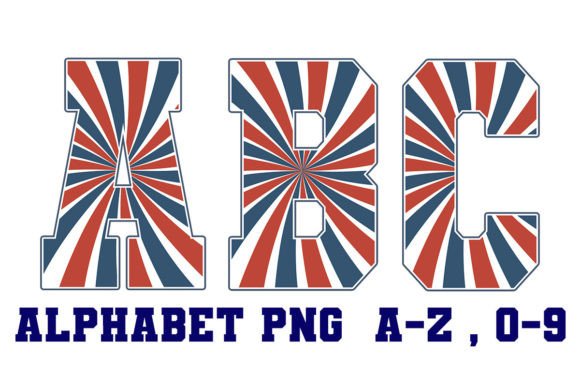
Retro Patriotic Alphabet Letters
Het vinden van de juiste ontwerpelementen kan lastig zijn, maar Retro Patriotic Alphabet Letters biedt een uitzonderlijke collectie die uw werk direct naar een hoger niveau tilt.